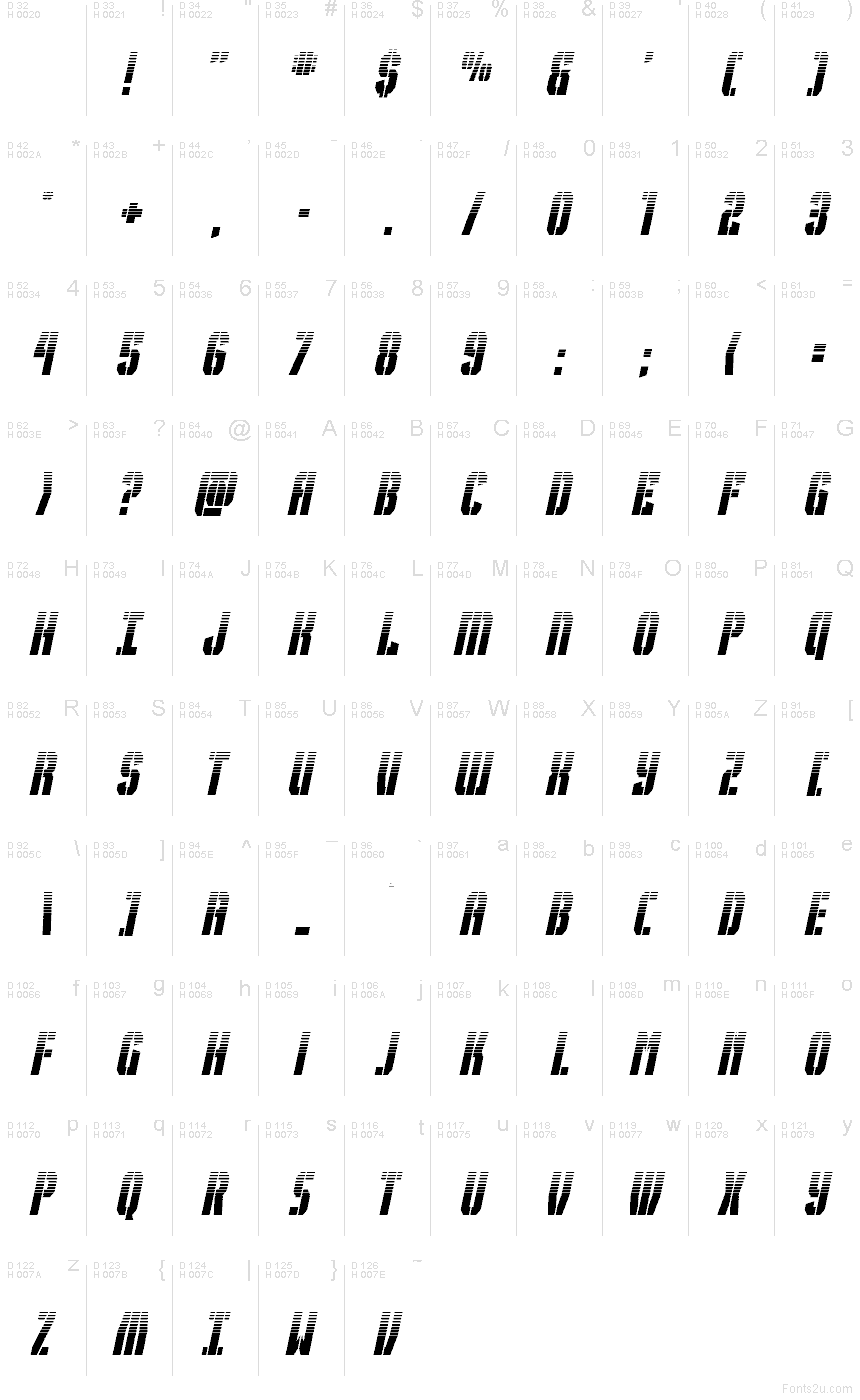
Gorilla Warfare Halftone Ital von Iconian Fonts ist ein kostenloser, vom Militär inspirierter Display-Font, der mit seinem harten, nach vorne geneigten Stil an gestempelte Dienstschriften erinnert. Die Versalien sind in fetten horizontalen Streifen gehalten, wodurch die Schrift wie eine schnelle Schablonen-Siebdruckarbeit wirkt, bei der stumpfe Formen und scharfe Diagonalen für die visuelle Power sorgen.
Er eignet sich hervorragend für Plakattitel, Gaming-Branding, Action-Filmplakate, Team-Grafiken und Event-Flyer – überall dort, wo ein kostenloser Font einen rauen Look braucht, ohne unsauber zu wirken. Da die Buchstaben durch Neigung, Streifen und Dynamik überzeugen, funktioniert der Font auch bei kurzen Titeln, Monogrammen und aggressiven Schlagzeilen.
Gorilla Warfare Halftone Ital